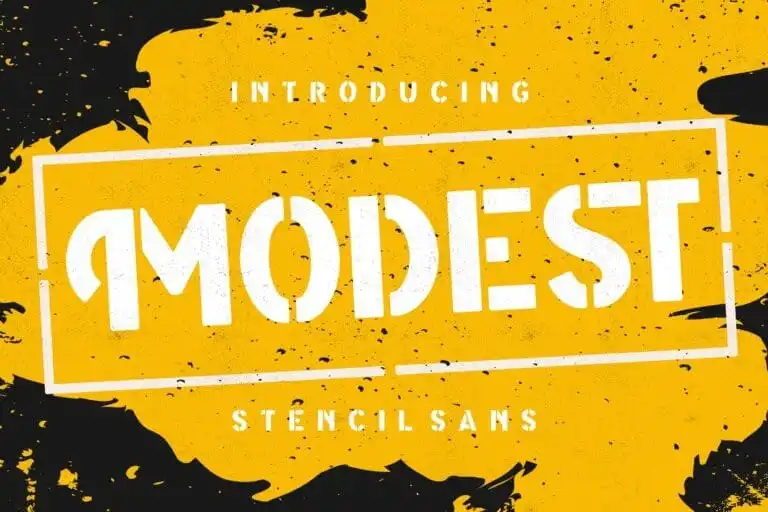
Modest Display Font
Modest Display Font é uma escolha perfeita para aqueles que buscam um estilo moderno e limpo sem perder a simplicidade e estilo clássico dos stencil. Desenvolvida pelo incrível designer Creatype Studio, esta fonte de exibição tem um design simples mas elegante. Ideal para criar visuais impactantes e intrigantes, Modest é perfeita para qualquer tipo de projeto gráfico que necessite de uma aparência minimalista e atrativa. Com seu estilo clássico dos stencil, essa fonte também pode ser usada em elementos como logotipos ou headlines, proporcionando um equilíbrio entre a modernidade da exibição e o design tradicional dos stencil. Seja para aplicações digitais, impressão ou até mesmo artesanato, Modest Display Font oferece uma versatilidade que torna-a um recurso indispensável para qualquer designer buscando criar designs impecáveis com estilo próprio.